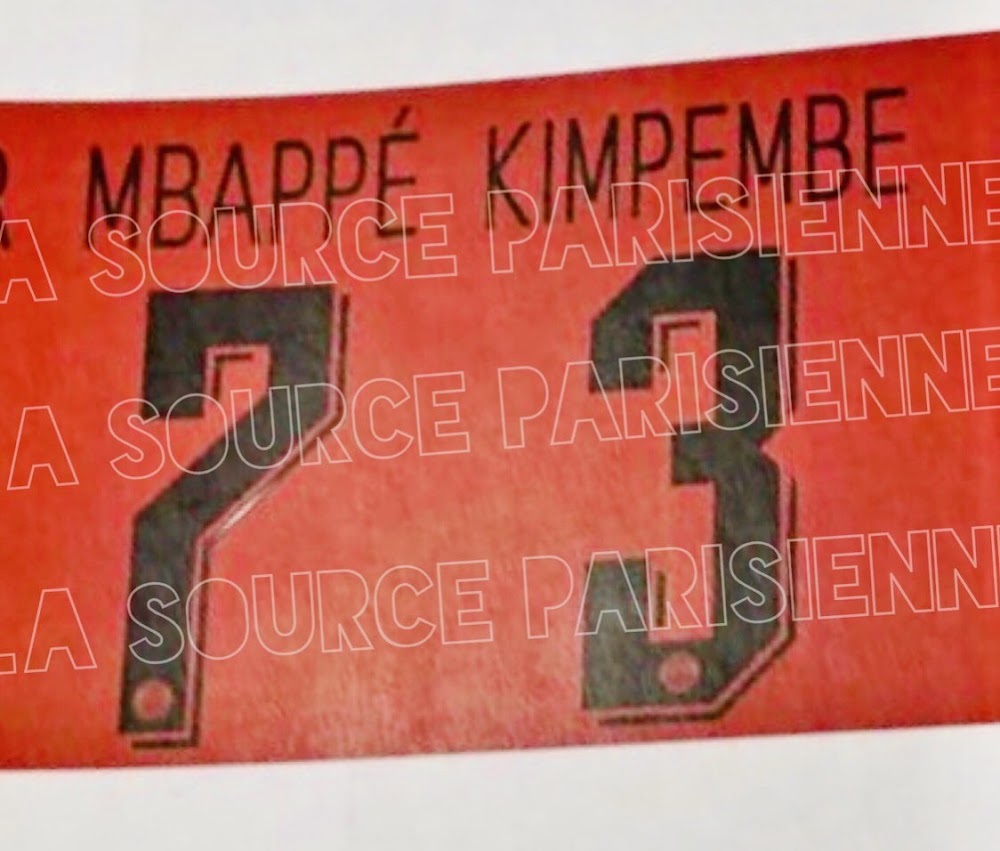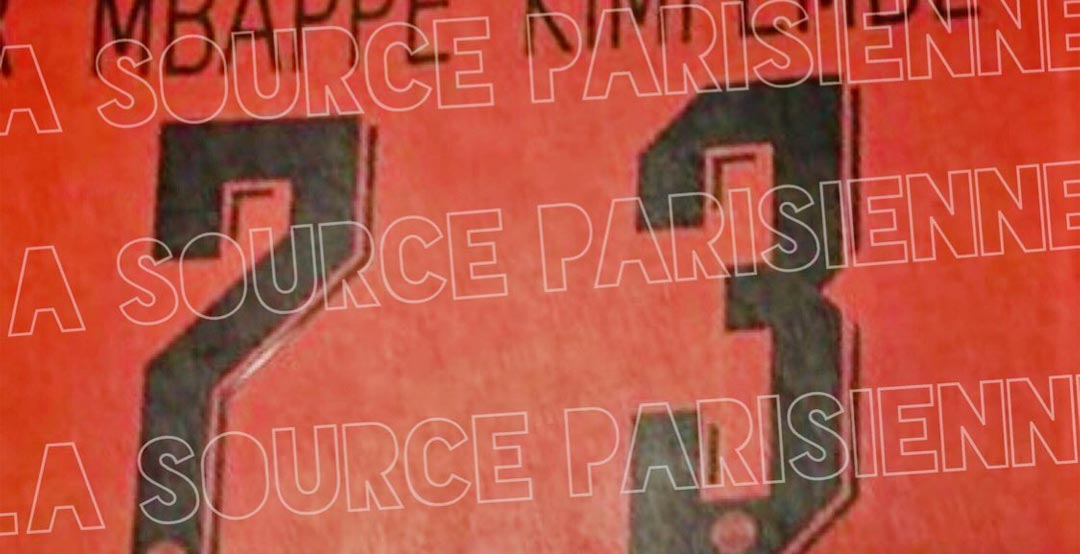
Einzigartige Jordan Paris Saint-Germain 19-20 Trikot-Schriftart Geleakt
Nike & Jordan haben eine einzigartige Schriftart für das Jordan Paris Saint-Germain 2019-2020 Trikot entworfen. Vielen Dank an den PSG-Experten la source parisienne für den Leak.
Jordan Paris Saint-Germain 19-20 Trikot-Schriftart
Die Schriftart des Jordan Paris Saint-Germain 19-20 Trikots ist eine moderne Kombination (Interpretation) aus klassischen Basketball- und Fußballschriften - sie kombiniert Elemente der berühmten klassischen Basketball- und Fußballschriften mit einem dreidimensionalen Effekt. Die Buchstaben der Schrift sind bemerkenswert dünn.
2018-19 Jordan PSG-Schriftart
Das PSG-Logo befindet sich am unteren Ende der Jordan Paris Saint-Germain 2019-2020 Trikot-Nummern.
2018-19 Jordan PSG-Schriftart
Die Schriftart für das Jordan Paris Saint-Germain 19-20 Trikot wird zusammen mit dem Auswärtstrikot im Juli 2019 veröffentlicht.